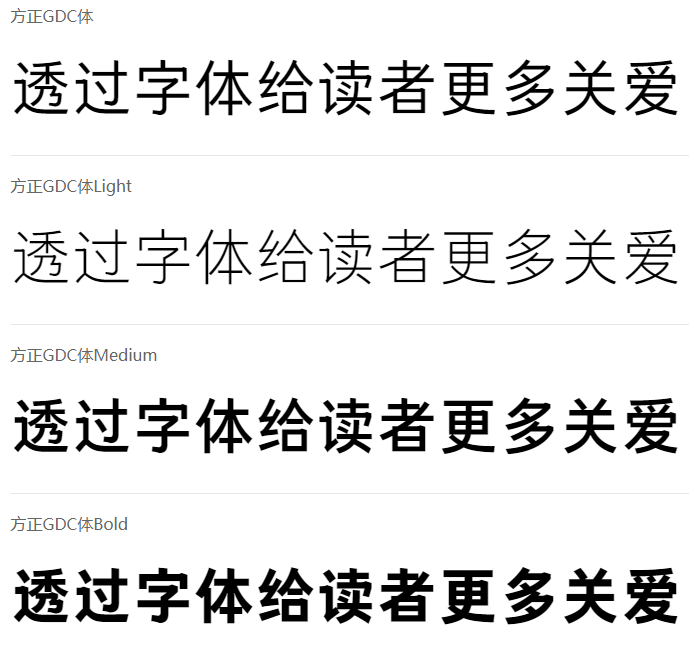
方正GDC体家族
设计师:仇寅,张昊,汪文
字体分类:黑体
方正GDC体家族
方正GDC体设计灵感来源于GDC奖奖杯竹节式的设计,挺拔、雅致而充满中国味。在设计中,我们也一直思考如何让奖杯的精神气质乃至形态特征融入这款专用字体。竹,自古有“节节高升”“宁折不屈”等象征。它“虚心”“直挺”的特点已成为世人所钟爱的君子品格。这样的感觉被吸纳进方正GDC体的设计:字面略窄、重心略高、内白舒适。 为满足GDC不同场景的应用需求,方正GDC体设计了四档字重,可以满足标题、正文使用需求。